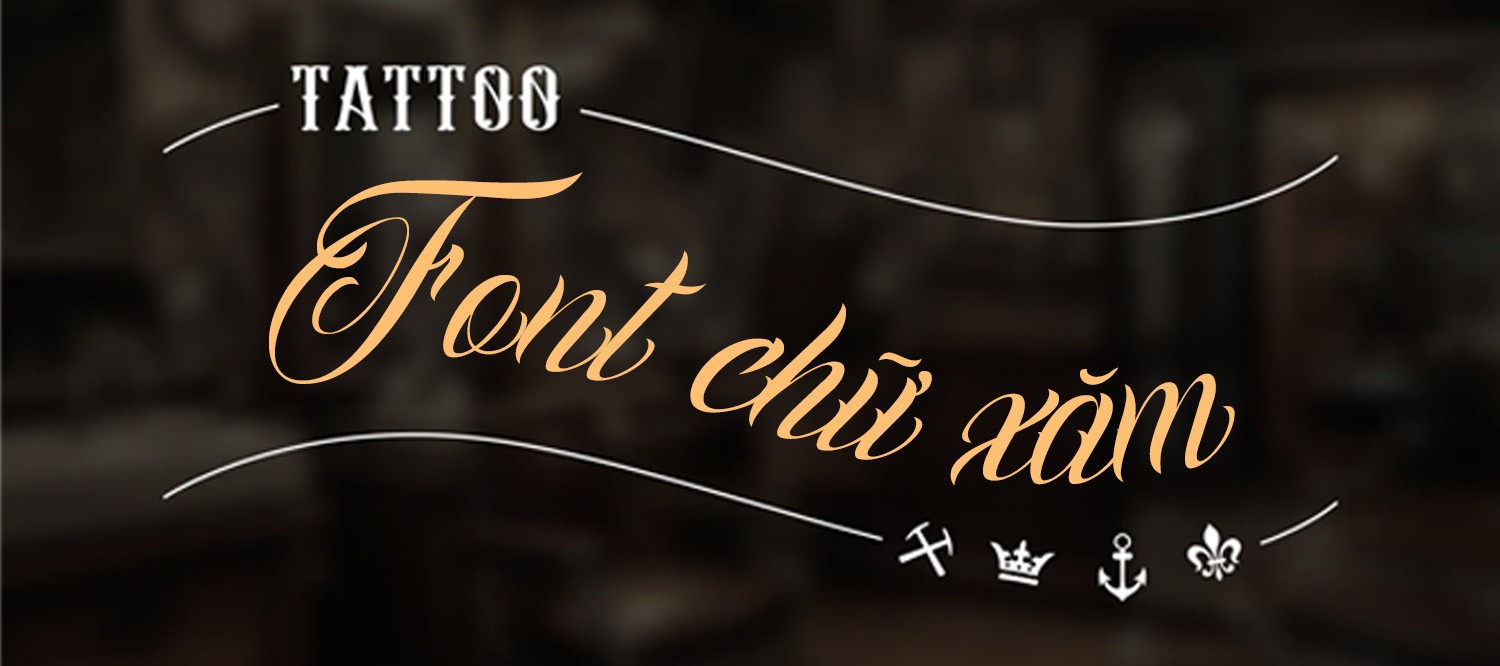
![[Tải xuống] Tổng hợp các font chữ xăm đẹp và độc đáo nhất cho thiết kế tattoo 2025](https://cdn.s99.vn/blog/fontxam2.jpg)
Font chữ xăm đã trở thành một phần không thể thiếu trong thế giới nghệ thuật xăm hình, giúp truyền tải thông điệp và cá tính của người xăm. Việc lựa chọn font chữ phù hợp cho một thiết kế hình xăm không chỉ giúp tạo nên ấn tượng thẩm mỹ mà còn góp phần thể hiện cá nhân hóa. Trong bài viết này, hãy cùng S99.vn khám phá top 10 font chữ xăm đẹp và độc đáo nhất cho những ai yêu thích nghệ thuật tattoo.
TH Alessa Beilaire Deluxe có kiểu chữ viết tay độc đáo, thể hiện được cá tính riêng biệt. Với các nét chữ mềm mại, uốn lượn, font chữ này tạo nên ấn tượng mạnh mẽ và đầy nghệ thuật. Mỗi ký tự đều có sự tinh tế và khác biệt, giúp các thiết kế hình xăm trở nên nổi bật và thu hút.
Font chữ này rất linh hoạt và dễ dàng kết hợp với các phong cách thiết kế khác nhau. Bạn có thể sử dụng TH Alessa Beilaire Deluxe cho những hình xăm đơn giản như tên riêng, câu châm ngôn hoặc thậm chí cho những thiết kế phức tạp hơn. Khả năng kết hợp với các yếu tố hình học hoặc họa tiết xung quanh giúp tạo nên một tác phẩm hoàn hảo và đồng bộ.
Font chữ TH Molahesta là lựa chọn hoàn hảo nếu bạn đang tìm kiếm một font chữ xăm đẹp và độc đáo để thể hiện cá tính riêng. Với nét viết tay mềm mại, uyển chuyển, font chữ này dễ dàng tạo nên những hình xăm ấn tượng và đầy cảm xúc. Đặc biệt, TH Molahesta rất phù hợp làm font chữ tạo hình xăm tên mình, giúp bạn thể hiện dấu ấn cá nhân một cách nghệ thuật và tinh tế. Mỗi ký tự đều được chăm chút kỹ lưỡng, vừa nhẹ nhàng vừa có điểm nhấn, làm nổi bật tên riêng của bạn một cách rõ nét, cuốn hút và đầy ý nghĩa.
Font chữ viết tay TH Manchester Signature là một sự lựa chọn tuyệt vời cho những ai đang tìm kiếm một kiểu chữ độc đáo, tinh tế và cá nhân hóa cho hình xăm của mình. Với sự phát triển và Việt hoá từ S99.vn, font chữ này không chỉ làm nổi bật tính thẩm mỹ mà còn truyền tải được cảm xúc và ý nghĩa sâu sắc trong mỗi tác phẩm.
Font chữ viết tay thường mang lại cảm giác cá nhân hóa cao, giúp mỗi hình xăm trở nên độc đáo và riêng biệt. TH Manchester Signature cho phép người xăm thể hiện được cá tính và câu chuyện của bản thân thông qua từng nét chữ. Điều này rất quan trọng trong nghệ thuật xăm hình, nơi mỗi tác phẩm thường mang một ý nghĩa sâu sắc và riêng tư.
Font chữ TH Viettay 3 là một trong những font chữ xăm đẹp, rất được ưa chuộng trong lĩnh vực nghệ thuật tattoo hiện nay. Với đường nét viết tay mềm mại, bay bổng, TH Viettay 3 giúp bạn dễ dàng sáng tạo các mẫu tattoo tinh tế, đặc biệt phù hợp cho việc xăm tên typo cá nhân hóa. Mỗi ký tự được thiết kế cẩn thận, điểm thêm những đường uốn lượn nghệ thuật, vừa nhẹ nhàng vừa cuốn hút. Nếu bạn đang tìm kiếm một font chữ đẹp, sang trọng để xăm tên hay tạo hình xăm độc đáo, TH Viettay 3 chắc chắn là sự lựa chọn lý tưởng để thể hiện cá tính riêng.
Font chữ Bibliophile Script là một trong những font chữ xăm đang được ưa chuộng nhờ nét chữ thanh mảnh, tinh tế đầy lôi cuốn. Mang phong cách viết tay uyển chuyển, mềm mại, Bibliophile Script đặc biệt phù hợp khi bạn muốn tạo hình xăm tên cá nhân độc đáo. Từng đường nét của font được thiết kế tỉ mỉ, điểm thêm những đường cong bay bổng, giúp mẫu tattoo của bạn nổi bật và ấn tượng.
SVN Bahud Aroyek là một font chữ cổ điển được sử dụng phổ biến trong nhiều lĩnh vực thiết kế, bao gồm cả nghệ thuật xăm hình . Đây là một font chữ có sức hút nhờ vào sự kết hợp giữa các đường nét cổ điển và sự uyển chuyển tinh tế, tạo nên sự ấn tượng và độc đáo cho bất kỳ tác phẩm nghệ thuật nào.
SVN Bahud Aroyek mang đậm chất cổ điển với các đường nét phức tạp và tinh xảo, phù hợp với những hình xăm mang phong cách hoài cổ hoặc những thiết kế có yếu tố lịch sử. Các chữ cái được tạo ra với sự chăm chút tỉ mỉ, tạo nên một cảm giác trang trọng và uy nghi. Phong cách cổ điển của font này rất phù hợp với các tác phẩm xăm mang tính biểu tượng, đặc biệt là khi người xăm muốn tạo ấn tượng mạnh mẽ và sâu sắc.
SVN Constreu Việt hóa là một trong những kiểu font chữ mang phong cách cổ điển, được ưa chuộng trong lĩnh vực thiết kế nói chung và đặc biệt là trong thiết kế tattoo. Với đặc điểm nổi bật là các đường nét dày dặn, mạnh mẽ và gợi nhớ về những thiết kế kiến trúc cổ xưa, font này mang đến vẻ đẹp uy nghi, sang trọng nhưng vẫn giữ được sự mềm mại nhờ vào cách tạo hình các ký tự.
Với nét chữ dày và đường nét sắc bén, SVN Constreu tạo ra sự nổi bật cho các thiết kế xăm lớn hoặc những phần xăm cần sự rõ ràng, mạnh mẽ. Đây là lựa chọn tuyệt vời cho các hình xăm mang tính tuyên ngôn hoặc thông điệp mạnh mẽ, giúp thu hút ánh nhìn và dễ đọc ngay cả từ khoảng cách xa.
Font chữ TH Mackenzin là một trong những font chữ tattoo đẹp rất được ưa chuộng nhờ thiết kế mạnh mẽ, cá tính. Mang phong cách font chữ cổ điển, TH Mackenzin sở hữu nét chữ sắc sảo, tinh tế và tỉ mỉ, phù hợp hoàn hảo để làm nổi bật các tác phẩm nghệ thuật trên cơ thể. Đặc biệt, khi sử dụng làm font chữ xăm, bộ font này dễ dàng tạo ấn tượng mạnh, mang lại sự sang trọng và đầy cuốn hút. TH Mackenzin chính là lựa chọn lý tưởng cho những ai muốn thể hiện cá tính riêng qua những mẫu tattoo độc đáo, đậm dấu ấn cá nhân.
Trong thế giới xăm hình, font chữ xăm là một phần quan trọng để thể hiện sự độc đáo và cá nhân hóa, vì vậy hãy cân nhắc kỹ khi lựa chọn để tác phẩm của bạn trở nên hoàn hảo nhất.